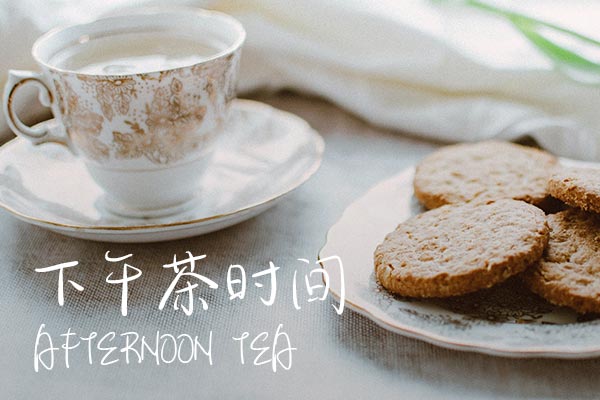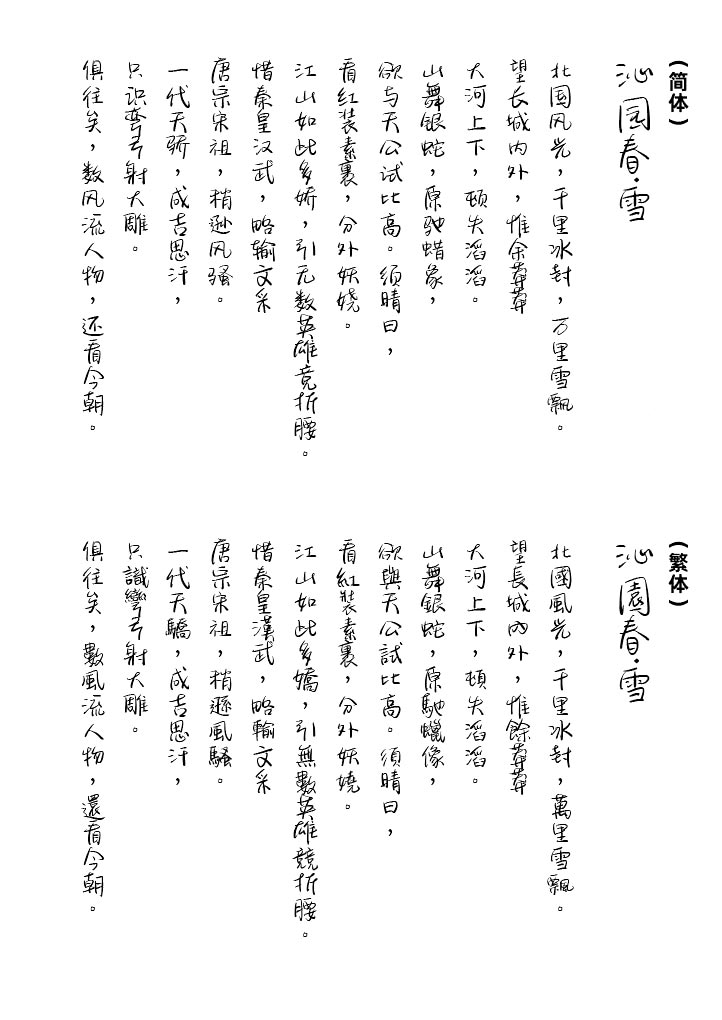
OZ焦糖下午茶
OZ焦糖下午茶是新蒂字体于2020年发布的一款专为个人与小型企业设计的免费商用字体。这款手写字体风格独特,活泼可爱,展现出清新与文艺的气息,适用于各种需要小清新、小文艺设计风格的作品。更重要的是,OZ焦糖下午茶支持超过10,000个简体字、繁体字及拉丁字母,字符集相当完善。
OZ焦糖下午茶效果预览
OZ焦糖下午茶字体效果预览